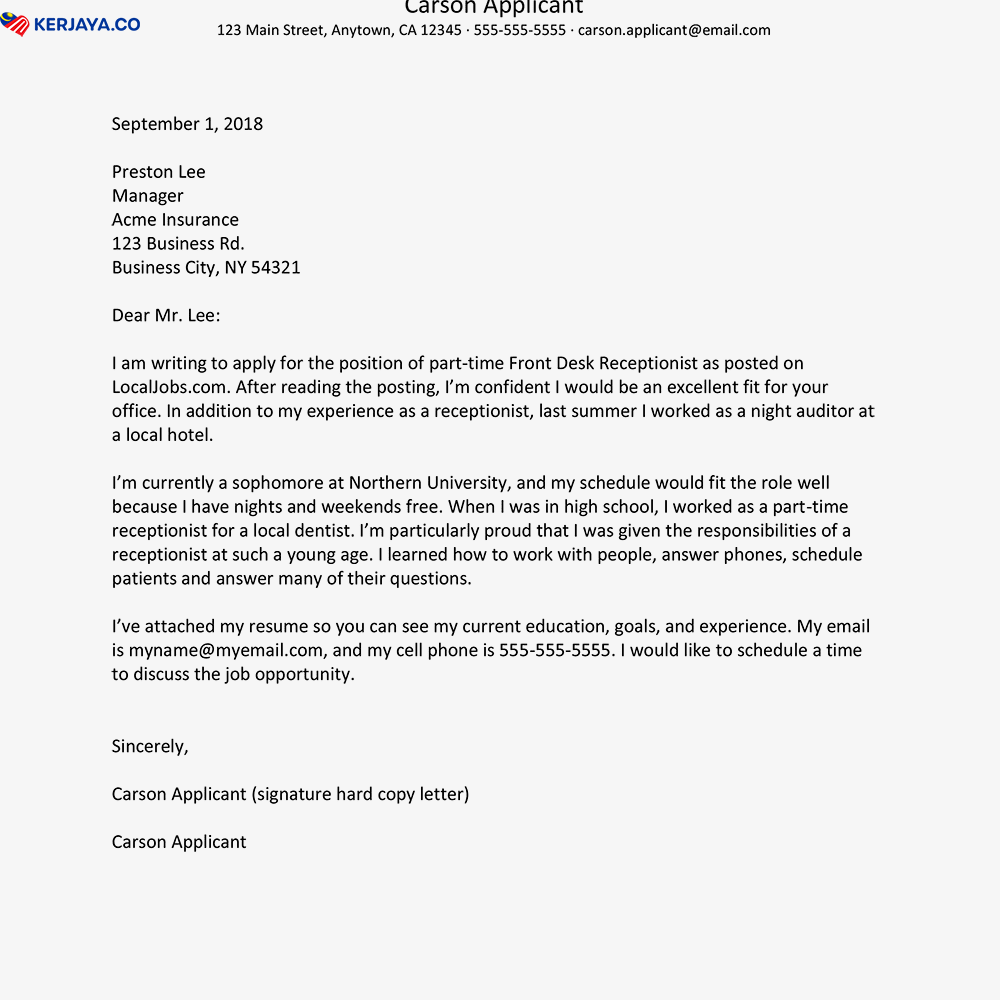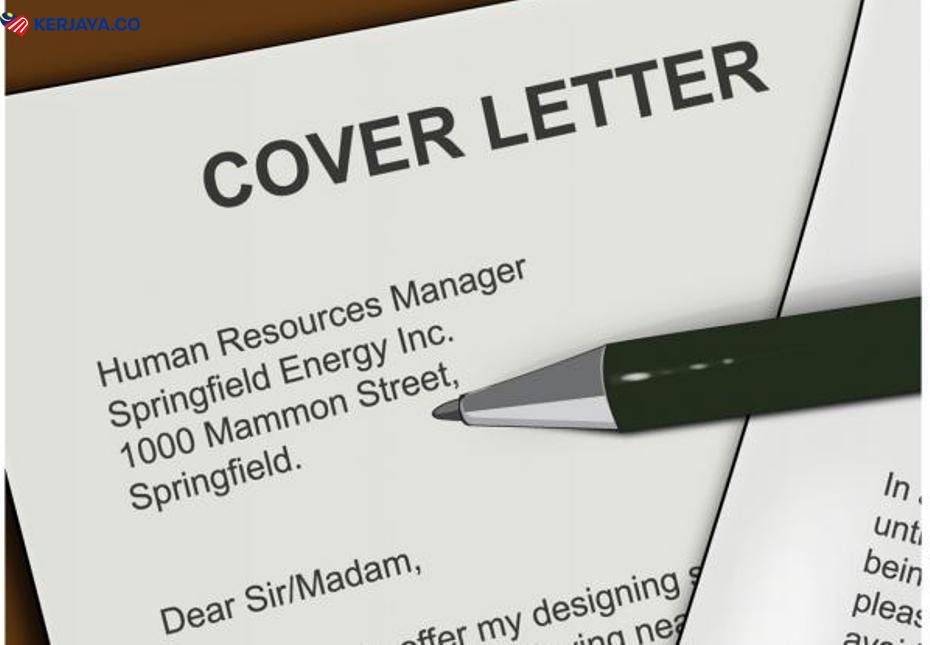
Font Dan Saiz Yang Sesuai Digunakan Untuk Cover Letter
Menulis cover letter bukanlah boleh dibuat dengan sambil lewa dan ikut suka anda sahaja. Anda perlu menulis dengan mengikut format yang sesuai dan pastikan majikan boleh membacanya dengan jelas.
Jadi, penggunaan font dan saiz yang sesuai sangat penting ketika anda menyiapkan cover letter anda.
Apakah font dan saiz yang sesuai untuk menulis cover letter?
Ringkas Dan Profesional
Walaupun anda seorang yang kreatif, elakkan menggunakan font yang tidak profesional seperti Comic Sans, Hand Writing dan sebagainya yang sukar dibaca oleh orang lain.
Tujuan utama anda menghantar cover letter adalah kerana untuk menyampaikan mesej yang jelas iaitu memohon pekerjaan dan sekaligus menonjolkan kemahiran serta pengalaman kerjaya anda.
Gunakan font dan saiz yang sama anda gunakan ketika menulis resume anda.
Font Dan Saiz Yang Sesuai Digunakan Untuk Cover Letter
Pilih Font Yang Ringkas
Anda boleh menggunakan font yang ringkas seperti Arial, Courier New, Calibri, Verdana, dan Times New Roman dan font jenis ini adalah yang terbaik untuk anda menulis resume anda. Ini kerana font ini mesra emel dan menjadi pilihan para profesional untuk menyiapkan cover letter mereka.
Pastikan juga anda menggunakan satu jenis font sahaja di dalam cover letter anda. Tidak perlu campur adukkan font. Anda juga dinasihatkan untuk tidak garis dan Italic perkataan sebaliknya gunakan Bold sekiranya anda ingin menonjolkan keywords tertentu.
Pilih Saiz Yang Betul
Anda boleh gunakan saiz font berukuran 10 hingga 12. Format cover letter anda dengan margin tidak lebih 1″ dan tidak kurang daripada 7″.
Saiz font juga bergantung pada jenis font yang anda gunakan. Sekiranya anda menggunakan font Arial, saiz 11 nampak sesuai kerana tidak terlalu besar dan tidak terlalu kecil serta mudah untuk dibaca.
Font Dan Saiz Yang Sesuai Digunakan Untuk Cover Letter
Cara Memilih Font Dan Saiz
Pilih font dari senarai di bahagian atas dokumen anda sebelum anda mula menulis cover letter anda, atau:
• Taipkan surat lamaran anda.
• Highlight kandungan surat anda.
• Pilih saiz font yang anda mahu gunakan dengan cara yang sama.
• Proofread atau baca semula cover letter anda.
• Print cover letter, walaupun anda akan upload melalui emel. Ini adalah untuk memastikan bahawa surat itu diformat dengan font dan saiz yang betul.
Pastikan anda telah memilih template yang sesuai sebelum menyiapkan cover letter. Kemudian cuba saiz dan font yang berbeza semasa menyiapkan cover letter. Selepas itu anda akan tahu font dan size yang mana sesuai untuk cover letter anda.
Font Dan Saiz Yang Sesuai Digunakan Untuk Cover Letter
Anda perlu mencuba setiap font dan saiz yang sesuai untuk menyiapkan cover letter. Jangan lupa untuk memasukkan keywords yang sepadan dengan jawatan yang dipohon.
Semoga perkongsian ini membantu anda menyiapkan cover letter dengan font dan size yang ideal.